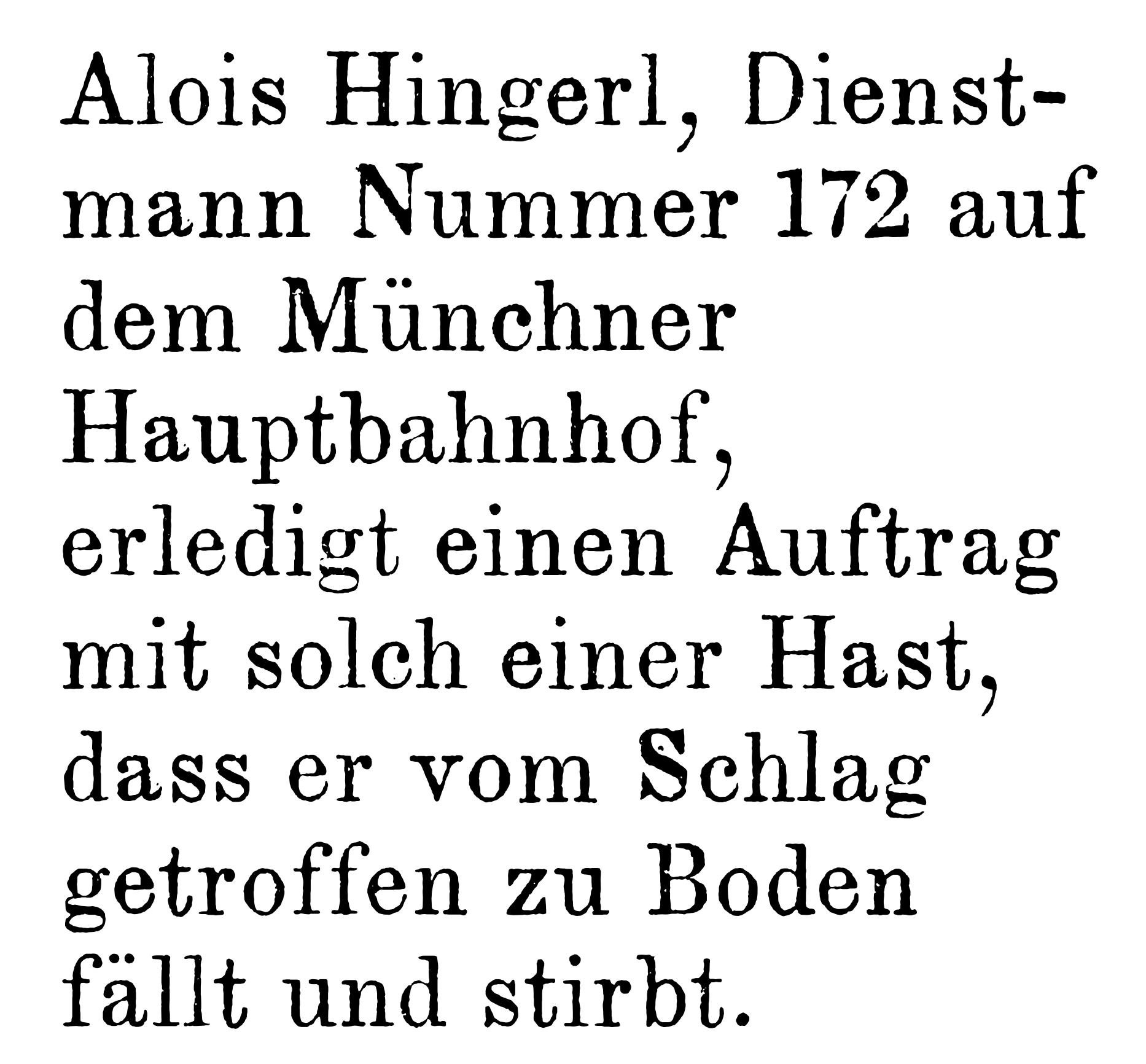
Font mit alternierenden Glyphen. Eine Frage.
für ein kommendes Semesterprojekt an der Burg Giebichenstein in der Fachklasse Buchkunst, würde ich gerne eine etwas ältere Idee endlich verwirklichen. Ein Font, welcher ein Sammelsurium aus verschiedenen Frakturschriften darstellt.
Wie ich in etwa die Glyphen herstellen kann, weiß ich bereits. (Natürlich werden auch Ratschläge hierzu dankend angenommen) Ich scanne alte Bücher ein und suche mir dann die einzelnen Buchstaben heraus, die ich verwenden will und wandle diese im Illustrator in Graphen um, etc.
Diese Schrift, welche bisher den Arbeitstitel Zeug trägt, soll dabei durchaus unsauber und abgestoßen daherkommen. Gleichzeitig darf sie sich quasi komplett aus Zwiebelfischen zusammensetzen.
Nun zu meiner Frage:
Ich würde den Font gerne so anlegen, dass alternative Glyphen zufällig gesetzt werden. Angenommen ich habe für jede Glyphe 5 oder 10 Varianten, dann sollten diese sich beim Eintippen zufällig abwechseln. Ist so etwas möglich und wenn ja, kann mir jemand sagen wie?
Willkommen, Friedrich. Im OpenType Schriftformat kannst Du ein kleines Script einbauen, das die verschiedenen Formen per Zufallsgenerator auswählt.  So habe ich es bei meiner WF Oldkirk gemacht, um mit jeweils sieben Variationen ein schludrig gedrucktes Schriftbild zu imitieren. Ich helfe Dir gerne dabei, wenn Du so weit bist.
Ist so etwas möglich und wenn ja, kann mir jemand sagen wie?
@catfonts hat einmal hier uns an der Entwicklung einer Schrift teilhaben lassen, bei der er auch eine Glyphenrotation programmiert hat. Ich glaube, es war eine Schreibmaschinenschrift. Ich finde jetzt grad den Thread dazu nicht, aber meine Erinnerung deutet mir an, dass er damals die Zufälligkeit nicht in den Font reinbekommen hat, sondern die Rotation nur zeilenweise alterniert werden konnte. Schau Dir einfach mal seine Beiträge hier an, die sind oft äußerst lehrreich!
Die von mir erinnerte Schrift ist diese hier: http://www.peter-wiegel.de/ErikasFarbband.html oder die hier: http://www.peter-wiegel.de/ErikasBuero.html
Da Catfonts seine Schriften so gut wie immer großzügig mit einer offenen Lizenz veröffentlichtlicht (GPL, OFL, ...) kannst Du die Schriften öffnen und Dir ihre Mechaniken anschauen.
Ja, richtig, Du darfst gerne Gebrauch dieser Schriften machen, ich hatte damals auch viel Hilfe hier im Forum bekommen. Zudem rotiere ich nicht nur durch die Glyphen, sondern benutze den jeweils erstem Buchstaben und dessen Code ala jeweiligen Startwert für die Rotation, und die geht nicht pro Zeile, sondern pro Ansatz. Dierdurch bekommer ich auch mehr Pseudo-Zufälligkeit, da ja kaum jeder Absatz immer mit dem gleichen Buchstaben startet.
Es gint zwar eine opentype-Funktion rand (zandom) aber die wird aus gutem Grund in keiner Software unterstützt, denn das würde dazu führen, dass der Text, jedesmal wenn er geöffnet wird quasi neu aus deiner Zeug-Kiste neu gesetzt wird, und da deine Glyphen dann wohl auch eine unterschiedliche Laufweite haben, und das würde bei tatsächlicher Zufälligkeit die Textlänge sich bei jedem Öffnen verändert, und das führ dann letztlich dazu, das ein komplettes Werk, so gesetzt bei jedem Öffnen eine andere Seitenzahl hätte, und keine Verweise und Inhaltsverzeichnisse mehr funktionieren.
Darum braucht man eine Technik, die ein hinreichend zufällig wirkendes Bild abgibt, aber doch immer zum gleichen Ergebnis führt. Zudem darf dieses OpenType-Script nicht zu groß werden, damit dann die Software, die dies beim öffen des Textes interprätieren muss dabai nicht aussteigt. Daher - nach auch zahlreichen Misserfolgen mein Kompromiss mit jeweis 9 Glyphen des gleichen Schriftzeichens.
Mein Tipp: Öffene eine der Erikas im Font-Editor und tausche da eingach nur die ganzen Glyphen-Outlines unter Beibehaltung der alten Glyphen-Namen aus, dann änderst du noch die Font-Info einträge und es sollte klappen.
Und dann lass mich deinen Font auch mal sehen :-)